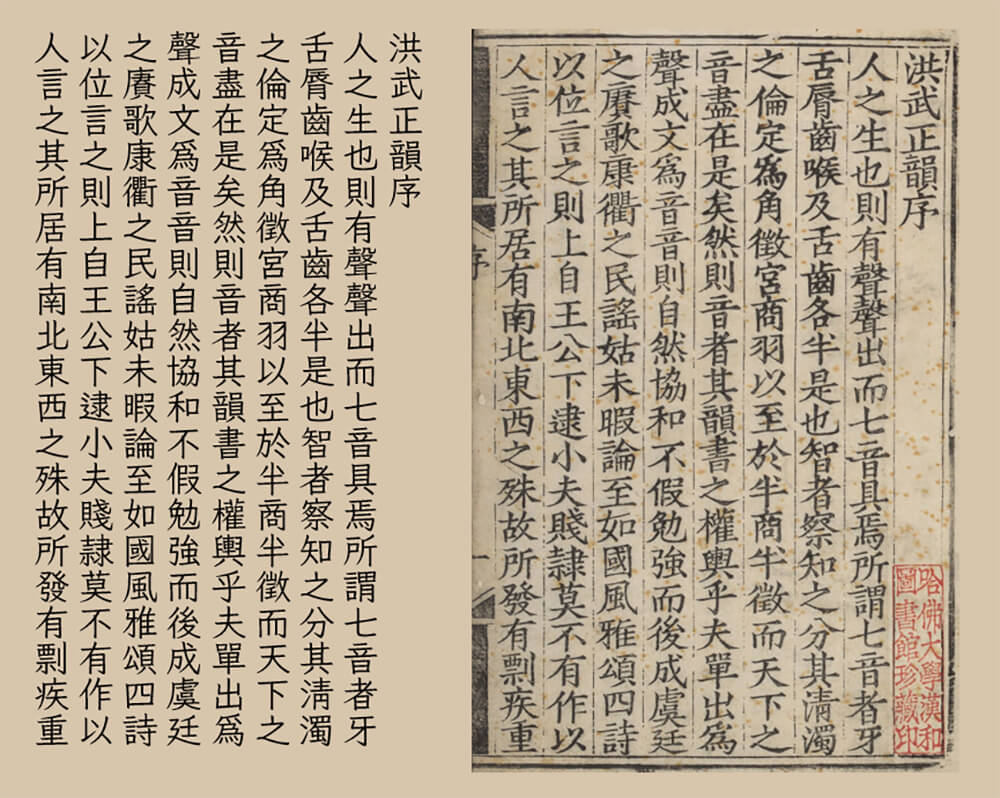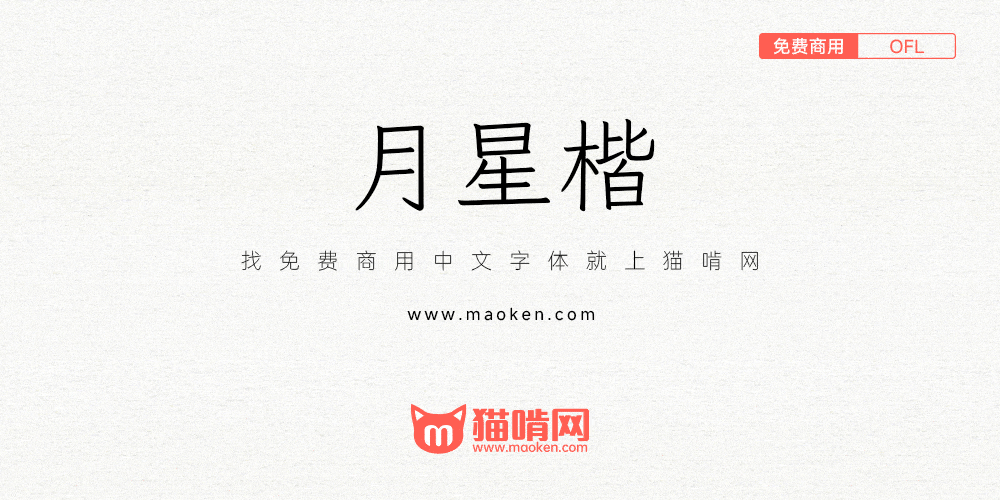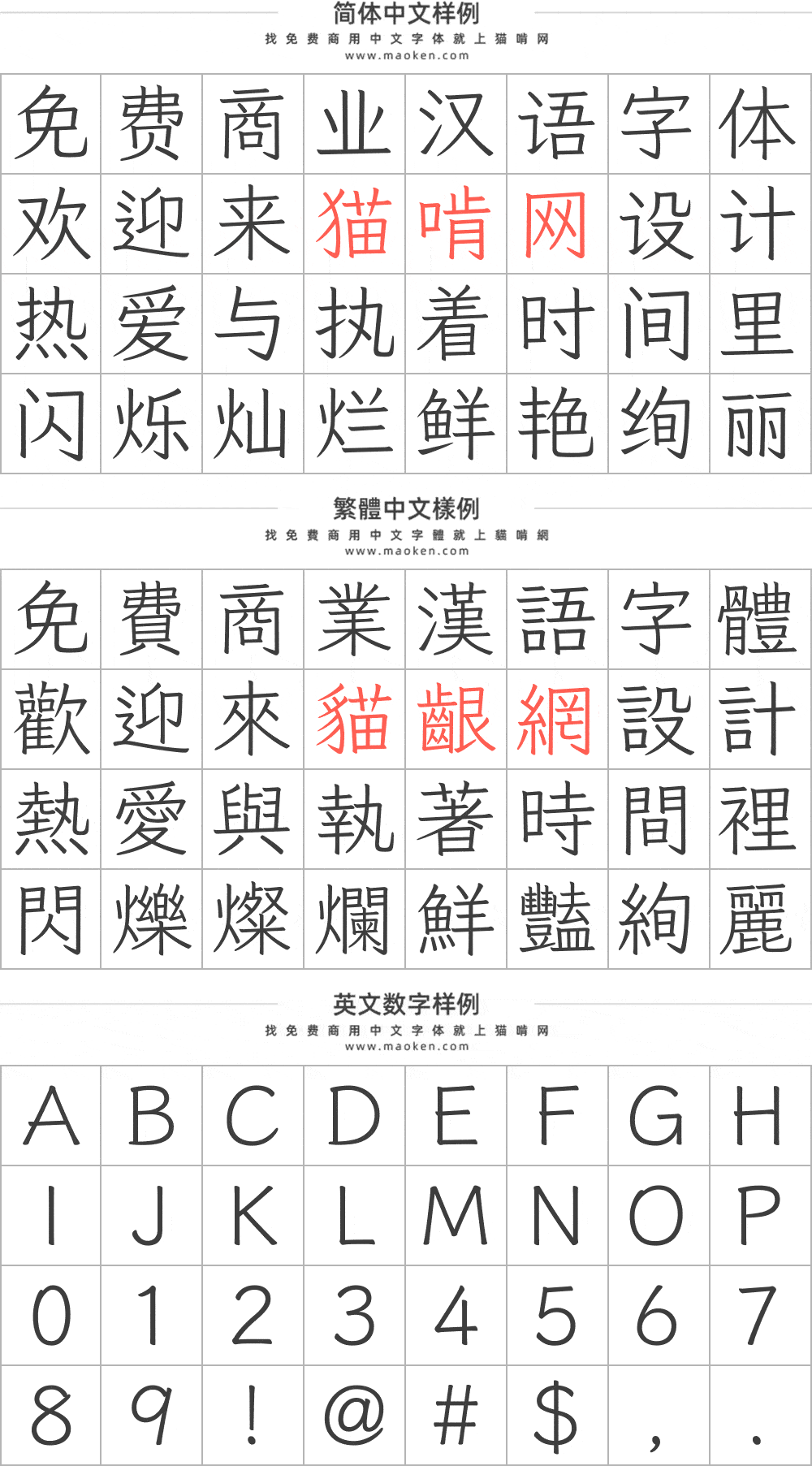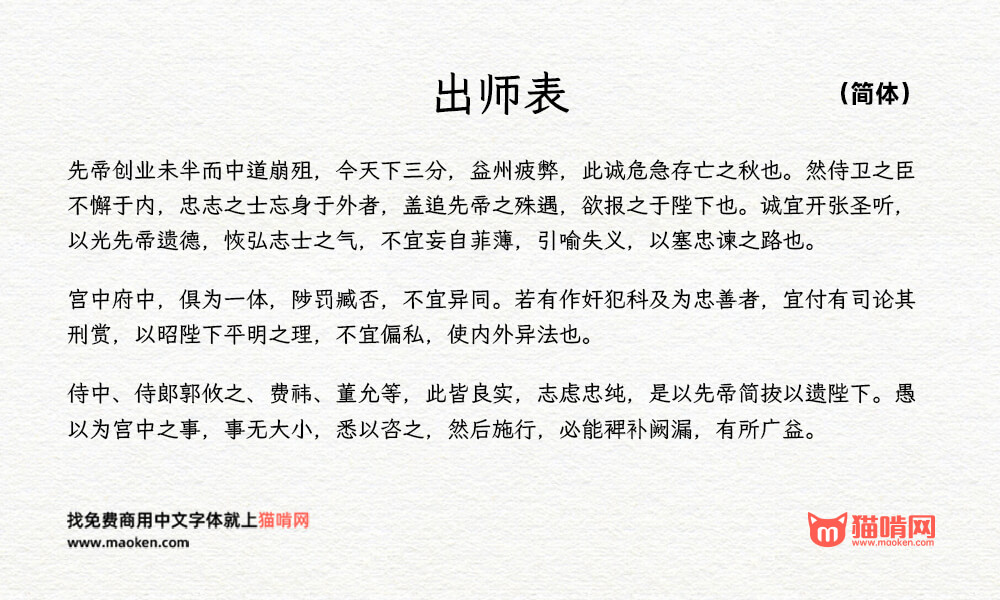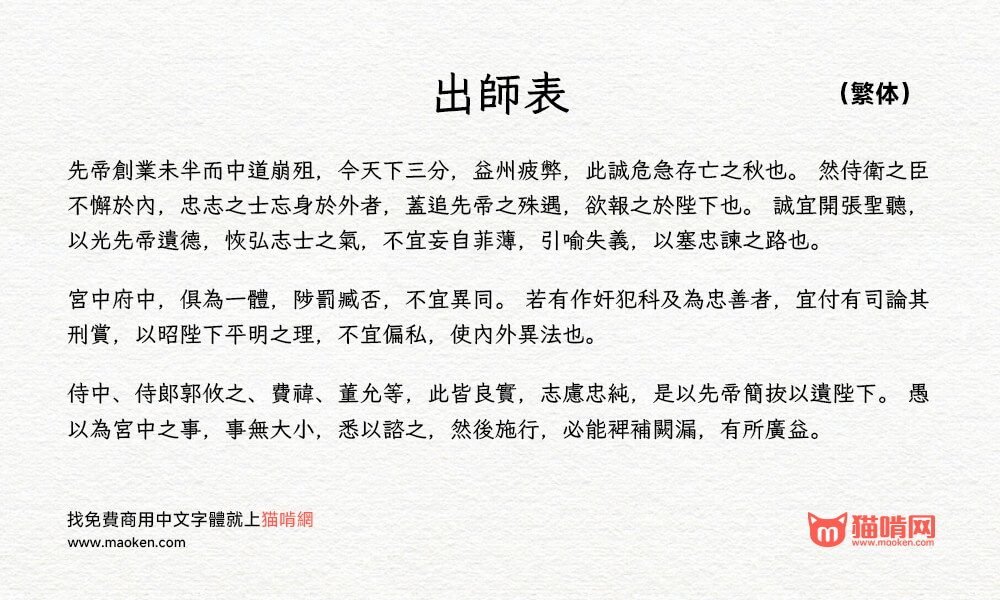
| 字体作者:GuiWonder (中国大陆) | 字体字重:1个 |
月星楷是一款由 Klee 衍生旧字形或古体字形风格的中文字体。作者GuiWonder在Klee One的基础上,结合霞鹜文楷 TC、霞鹜文楷以及芫荽字形,参照《洪武正韵》(明嘉靖四十年刘以节刊本)制作。部分字形在现代书写中已经很少见,但可常见于书法字贴。
T 月星楷 繁由月星楷修改,简入繁出的字体。此字体使用了 OpenType 功能,可根据文本内容动态匹配一简多繁的情况。
- 「艹」部件改用四筆(即「十十」),部件來自芫荽。
对于简体用户来说,这个字体非常有迷惑性。
它其实 完全是为了 古文 而制作的。
虽然 看起来 很多简体字 很不错,而且 统计上 覆盖了 常用的所有简体字,但是——
有大量的字符,默认显示为古文的字形。在笔画结构甚至笔画数量上,都与现代简体字不同。
它有两个变体版本:“月星楷”和“月星楷 繁”。
后者是完全的繁体字版本,但前者却是一个杂交品种——笔画简化+古代写法……
输入“欢迎读者”,你会看到:
– “迎”和“者”都多了一个点,与我们的简体字写法不同,因为这是古代的写法。
– 在“月星楷 繁”中“欢”显示为“歡”、“读”为“讀”。
我不知道什么样的用户需求,会需要输入简体字符,却要看到古文的字形。
但我知道,普通的简体用户,应该想要的是看到现代简体字的字形。
虽然这个字体支持“异体字选择器”(Unicode的一个高级机制),从而可以 针对单个字符指定呈现为哪种字形,但对于普通用户来说,使用成本实在太高了,近乎不可能。
所以,简体用户可以放弃了。